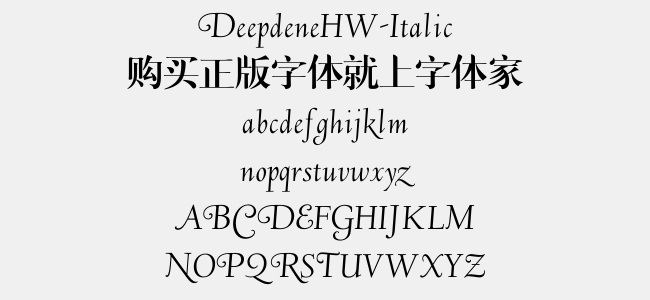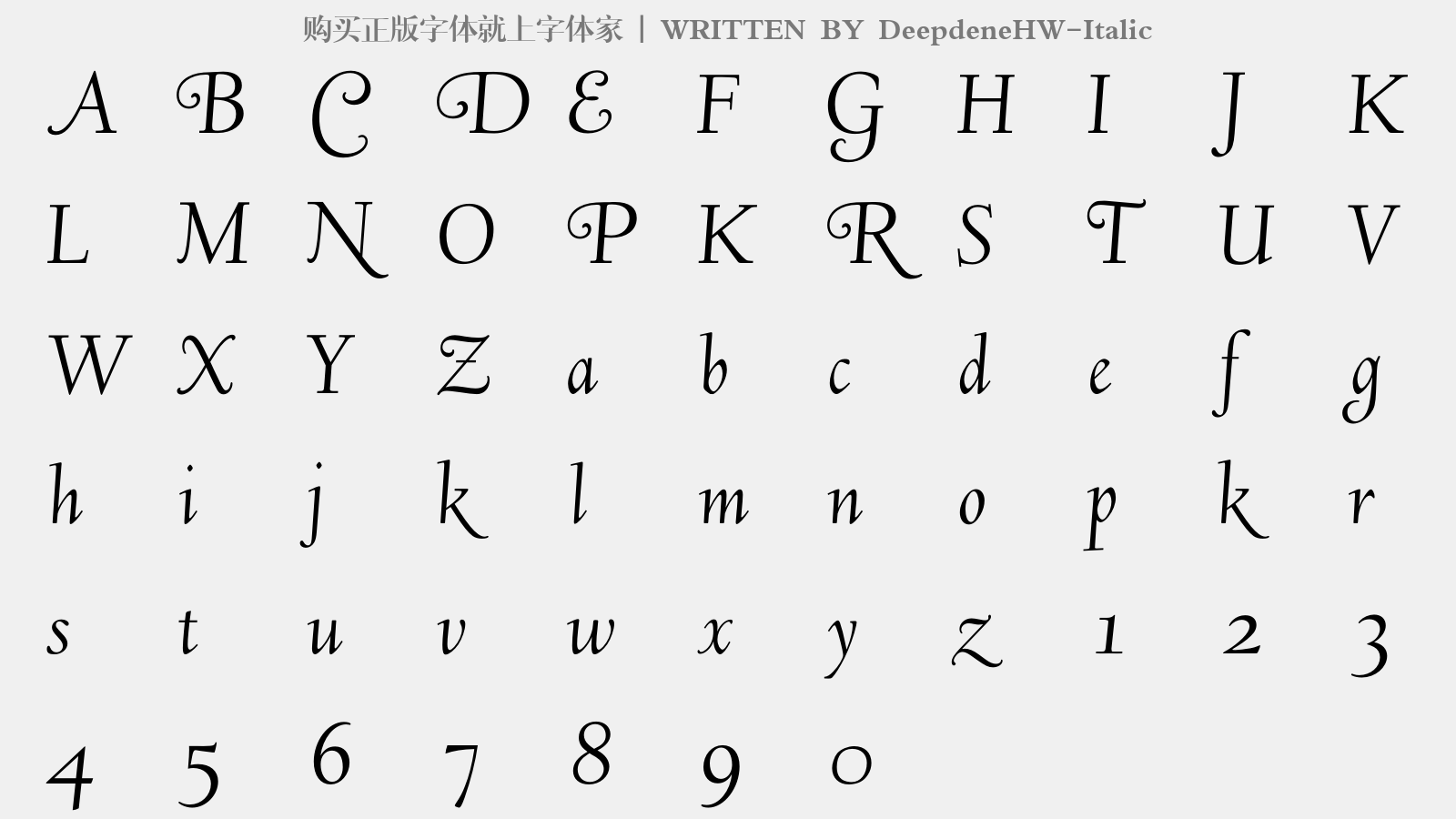
DeepdeneHW-Italic
字体名称:DeepdeneHW-Italic
字体字数:26个英文大小写字母及和阿拉伯数字
书体类型:英文类
DeepdeneHW-Italic
该字体是一款个性独特的英文字体,非常适合创意类的PS字体,英文广告设计载体上使用,在设计中选择这款字体应用的话,会起到非常理想的效果。